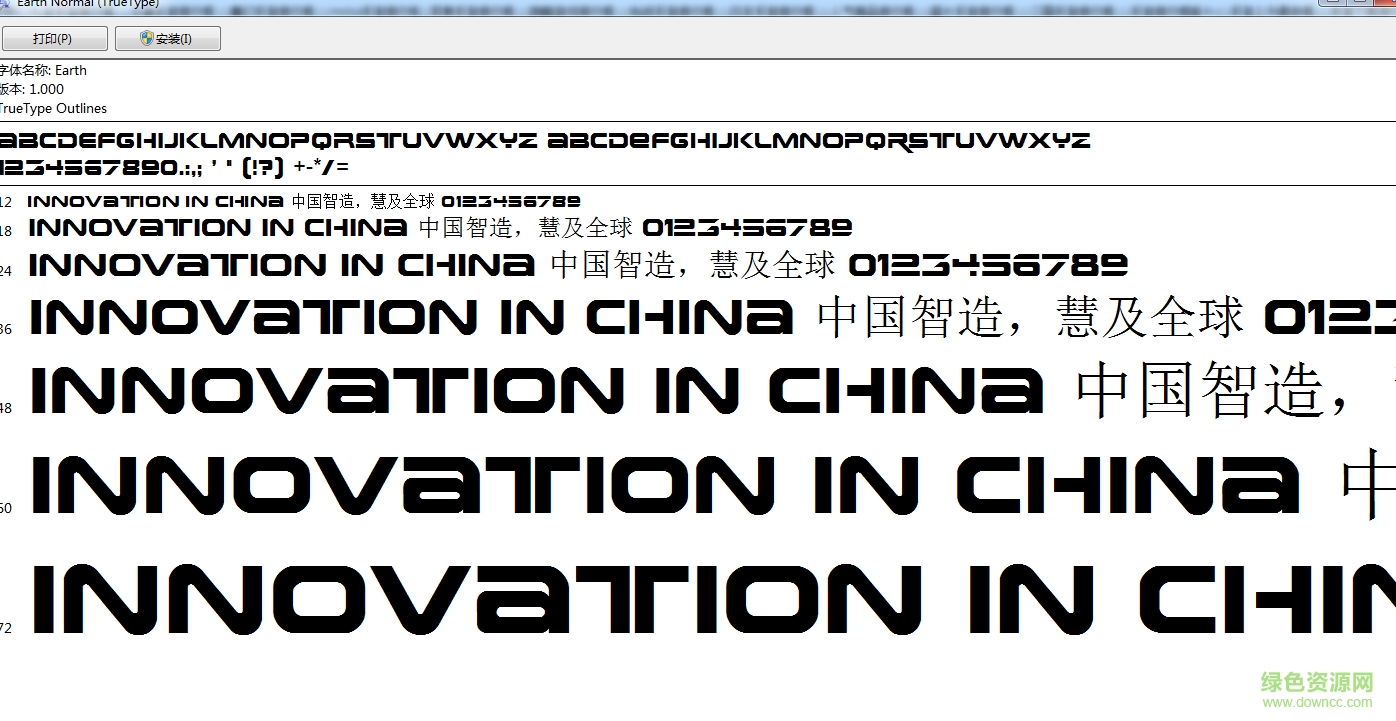
earth normal字體是一款粗黑莊重的英文字體,字型飽滿,結(jié)構(gòu)穩(wěn)定,氣勢(shì)雄健,用作文章大標(biāo)題或宣傳標(biāo)語(yǔ)效果都非常醒目。有需要者歡迎在綠色資源網(wǎng)下載!
字體造型規(guī)整,富于力度,給人以簡(jiǎn)潔爽朗的現(xiàn)代感,有較強(qiáng)的視覺(jué)沖擊力,這種個(gè)性的字體,適合于機(jī)械科技等主題。
earth字體印刷效果清晰明快,可用于文章 標(biāo)題、廣告制作、裝飾裝幀等。